随着时代的更新变换,网络科技已经与人类必不可分了,字体师的也是人们工作生活的重要部分之一,每天都会接触它、使用它。一款字体的诞生,要经过字体设计创意设计、字体制作人员一笔一划的制作、修改等多个技术环节。我们使用的字体都是设计师费劲心血设计而成的,接下来为大家介绍几款不同种类的优秀字体设计作品。
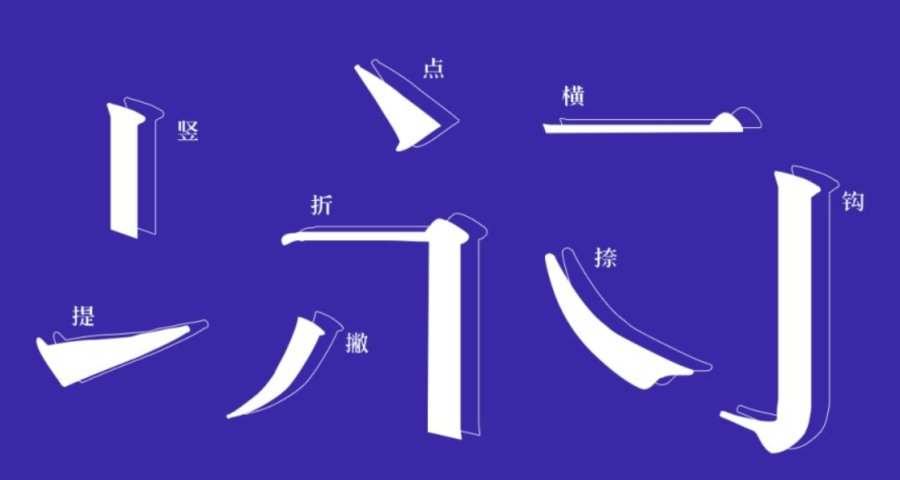
在中文字体里不可不说的就是宋体字,一般较为雅致、大气、正统,给人一种古香古色的感觉,有一种永恒的美,通用性很高。这款“印品铸宋体”在传统宋体字的基础上做出了细节化的整改,设计师在古色古香的味道上融合了新时代气息。字体线条刚劲有力,笔画张弛有度。不同于系统化的宋体字,在保持字体识别性的基础上进行大胆的艺术创作新颖别致。
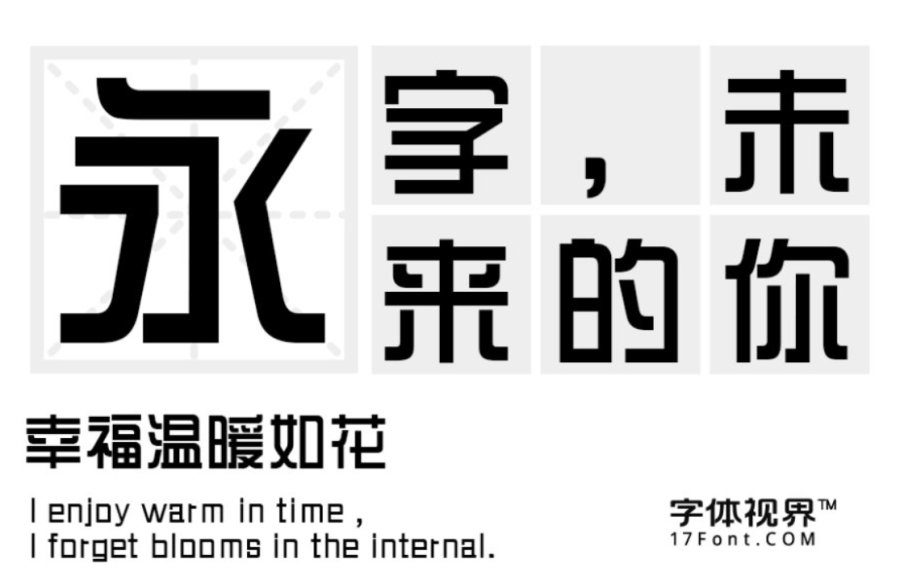
刚刚给大家介绍了较为古风的宋体,现在给大家介绍较为现代感的综艺字体。这个种类的字体通常在笔画转折处进行了圆角的处理,使字体柔中带刚,稳重有力且不失柔和,简简单单就可以传达出艺术、专业、现代感。上图这款“三极综艺简体100”结构严谨,字型修饰得宜,恰到好处,整体规范而不失特色。严谨秀气而从容和优雅,让人赏心悦目,百看不厌。可广泛用于书刊、广告、包装、店招、影视以及社交网络个性化用字。
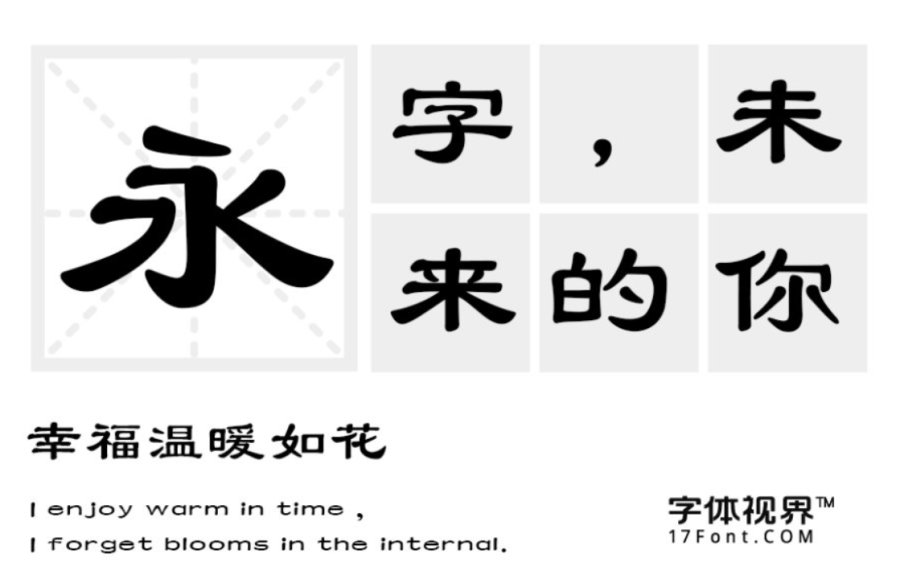
中国的书法字体在中文字体中举足轻重,隶书是中国汉字中常见的一种庄重的字体,书写效果略微扁宽,横画长直画短。这款“三极隶书简体”以传统隶书的结构为本并融于隶书笔形特征设计而成,其笔画横长竖短,平稳均匀,字形轮廓扁方统一,收放自如。这款字适用于各类传统纸媒,书法作品排版及适用于传统古典类标题、招牌设计。